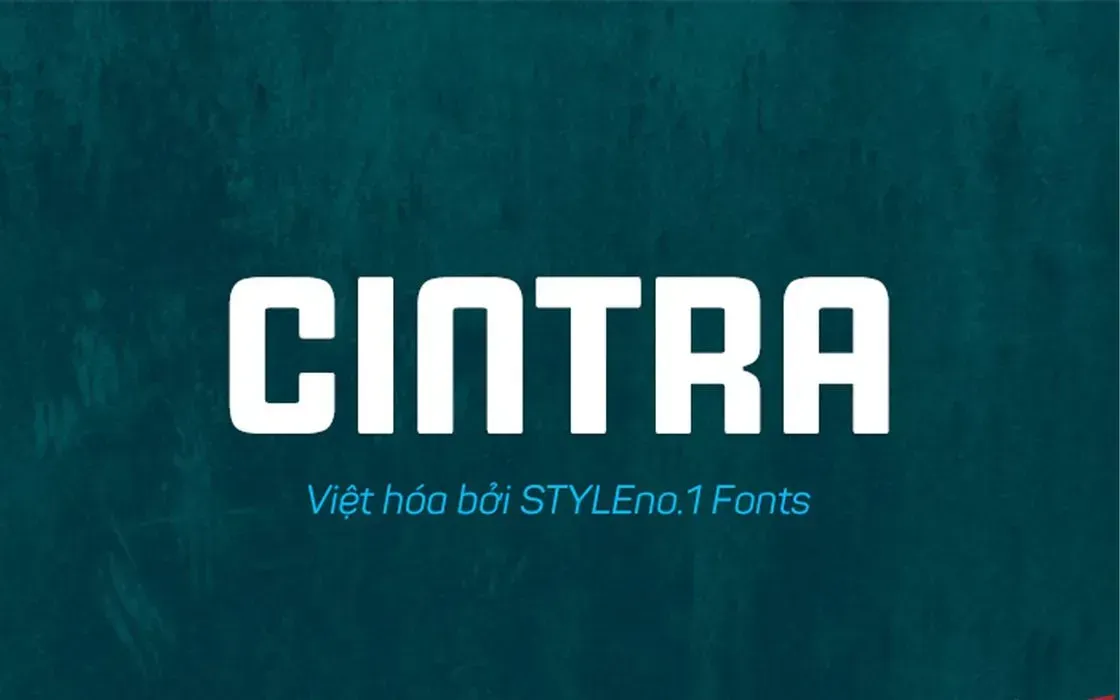
SVN Cintra là một kiểu font sans-serif (không chân) mang phong cách công nghiệp, hiện đại và chắc chắn, nổi bật với các đường nét hình học dứt khoát, vuông vức và mạnh mẽ. Từng ký tự trong font được thiết kế với sự chính xác cao, tạo cảm giác kỹ thuật, rõ ràng và có phần nghiêm túc, rất phù hợp với các thiết kế cần truyền tải tính chuyên môn, công nghệ hoặc kiến trúc.
Font gốc Cintra được phát triển bởi LeFly Fonts, lấy cảm hứng từ các cấu trúc kỹ thuật, bảng vẽ công trình và giao diện máy móc. Kiểu chữ này có phần góc cạnh, ít bo tròn, tạo ấn tượng về tính hệ thống và kỷ luật, khiến nó trở nên lý tưởng cho những ngành như xây dựng, kỹ thuật, phần mềm, công nghiệp, tài chính.
Bản Việt hóa bởi nhóm SVN Fonts được tinh chỉnh tỉ mỉ để bổ sung đầy đủ dấu tiếng Việt, đồng thời giữ nguyên các tỉ lệ và hình dáng đặc trưng của bản gốc, đảm bảo tính thẩm mỹ và khả năng ứng dụng rộng rãi trong thiết kế tiếng Việt. Font hoạt động mượt mà trên các phần mềm như Photoshop, Illustrator, InDesign, Canva, Figma...
– Thiết kế logo công nghệ, kỹ thuật số, công nghiệp
– Giao diện website, ứng dụng quản lý, bảng dashboard
– Tiêu đề hồ sơ doanh nghiệp, tài liệu kỹ thuật, biển chỉ dẫn
– Bao bì sản phẩm mang hơi hướng minimalist – technical – futuristic
Nếu bạn đang cần một font không chân, mạnh mẽ, công nghiệp nhưng vẫn hiện đại và dễ đọc, thì SVN Cintra chính là lựa chọn lý tưởng để mang lại cảm giác vững chãi, chuyên nghiệp và hiệu quả thị giác cao trong mọi thiết kế.